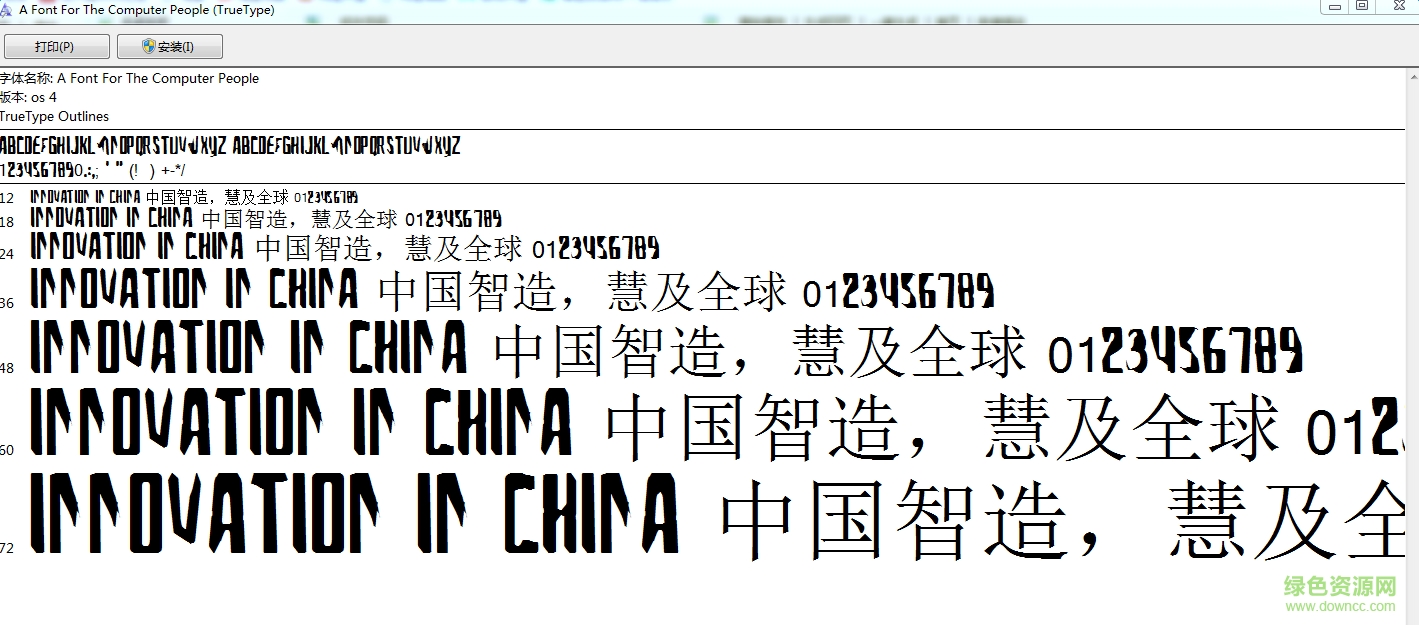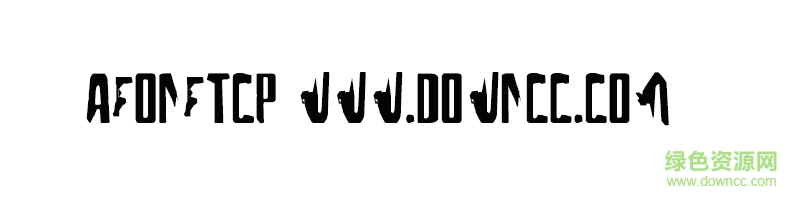
Afonftcp字體是一款A(yù)fonftcp風(fēng)格英文字體軟件,Afonftcp風(fēng)格的字體給人非常正規(guī)的感覺,深受廣大年輕人的喜愛,還有更多好看字體盡情期待,歡迎到綠色資源網(wǎng)下載體驗(yàn)!
Afonftcp是一款A(yù)fonftcp風(fēng)格英文字體,字體效果比較正規(guī),喜歡英文體字的朋友可以下載使用看看效果如何。